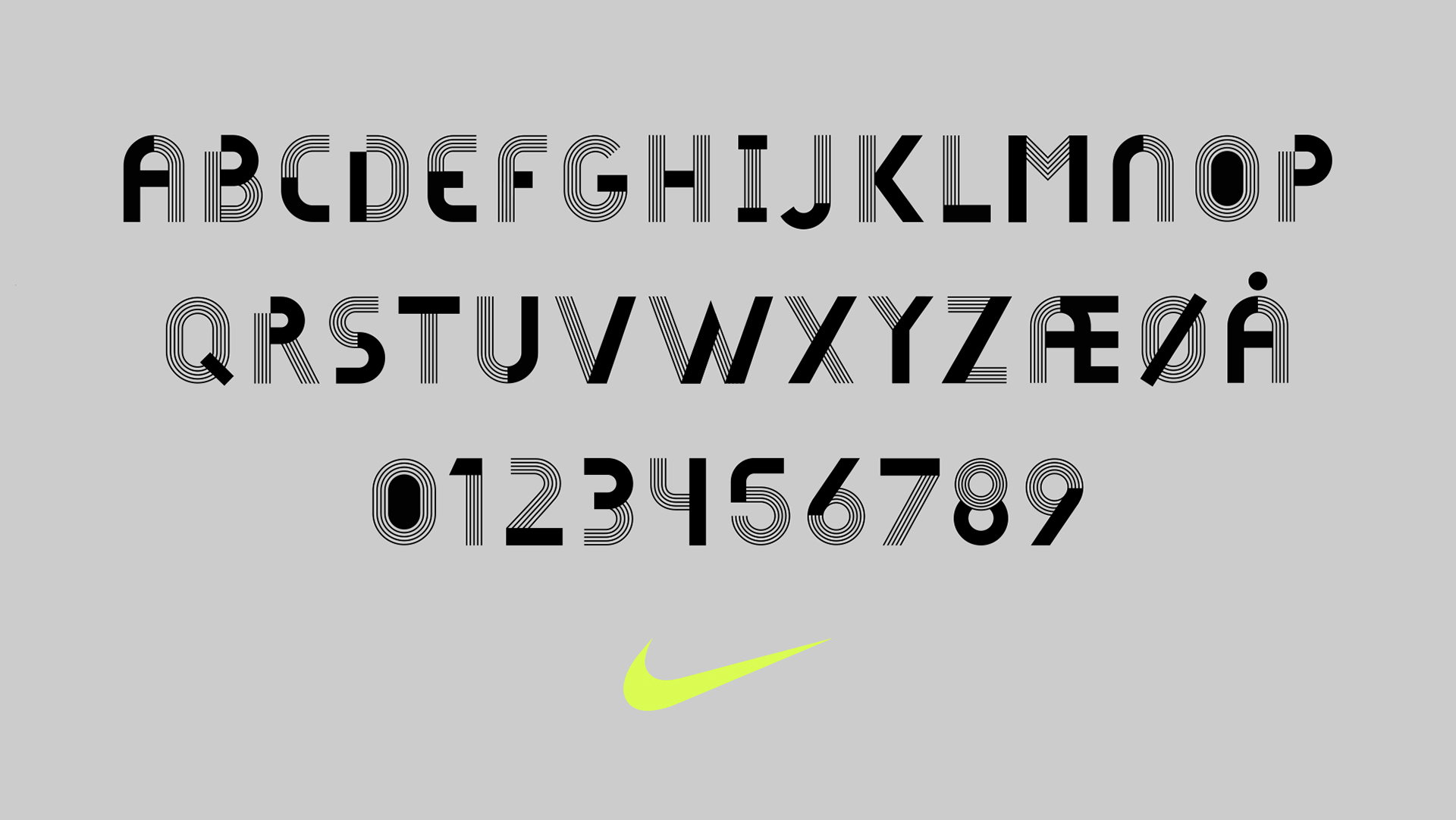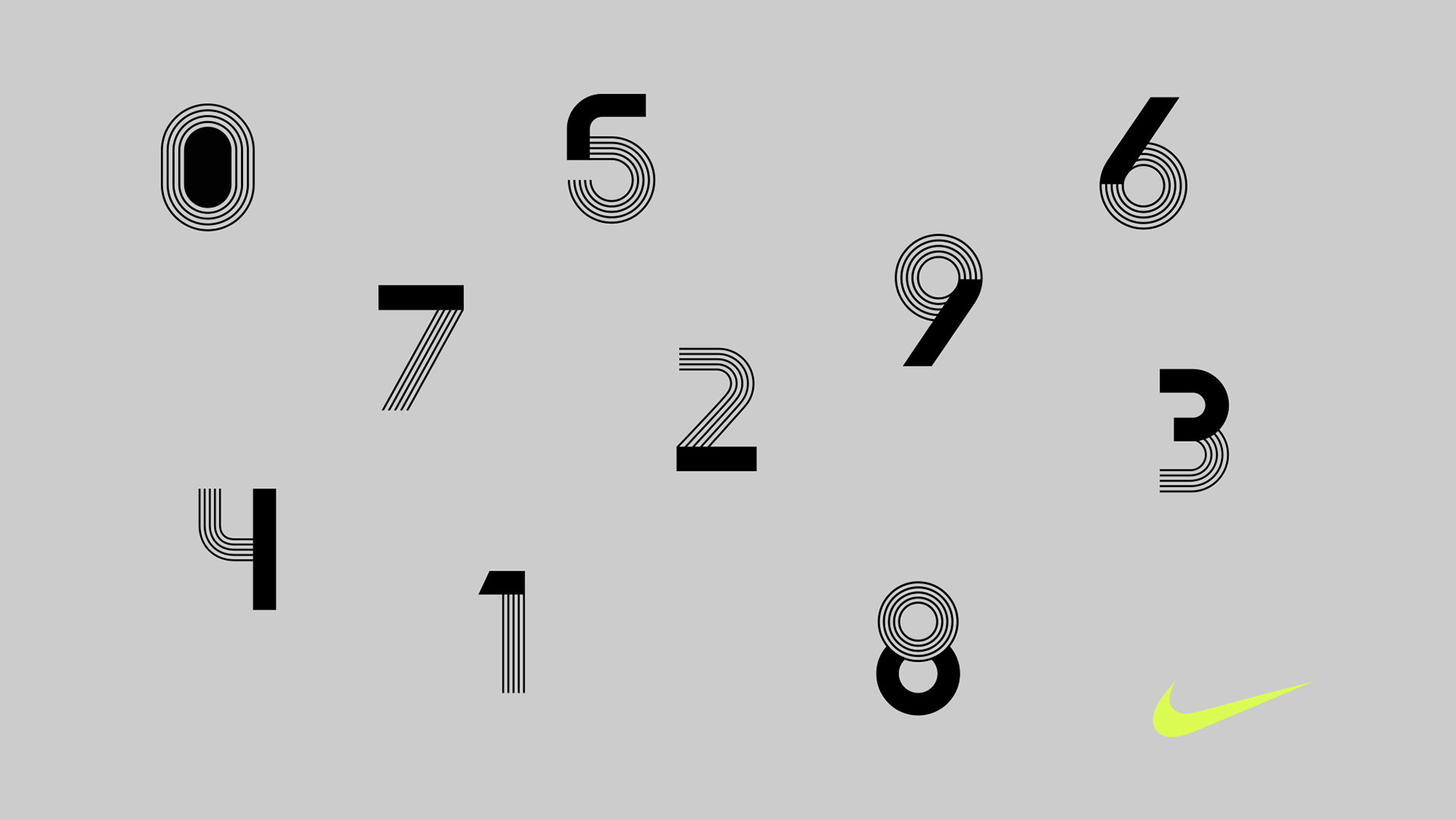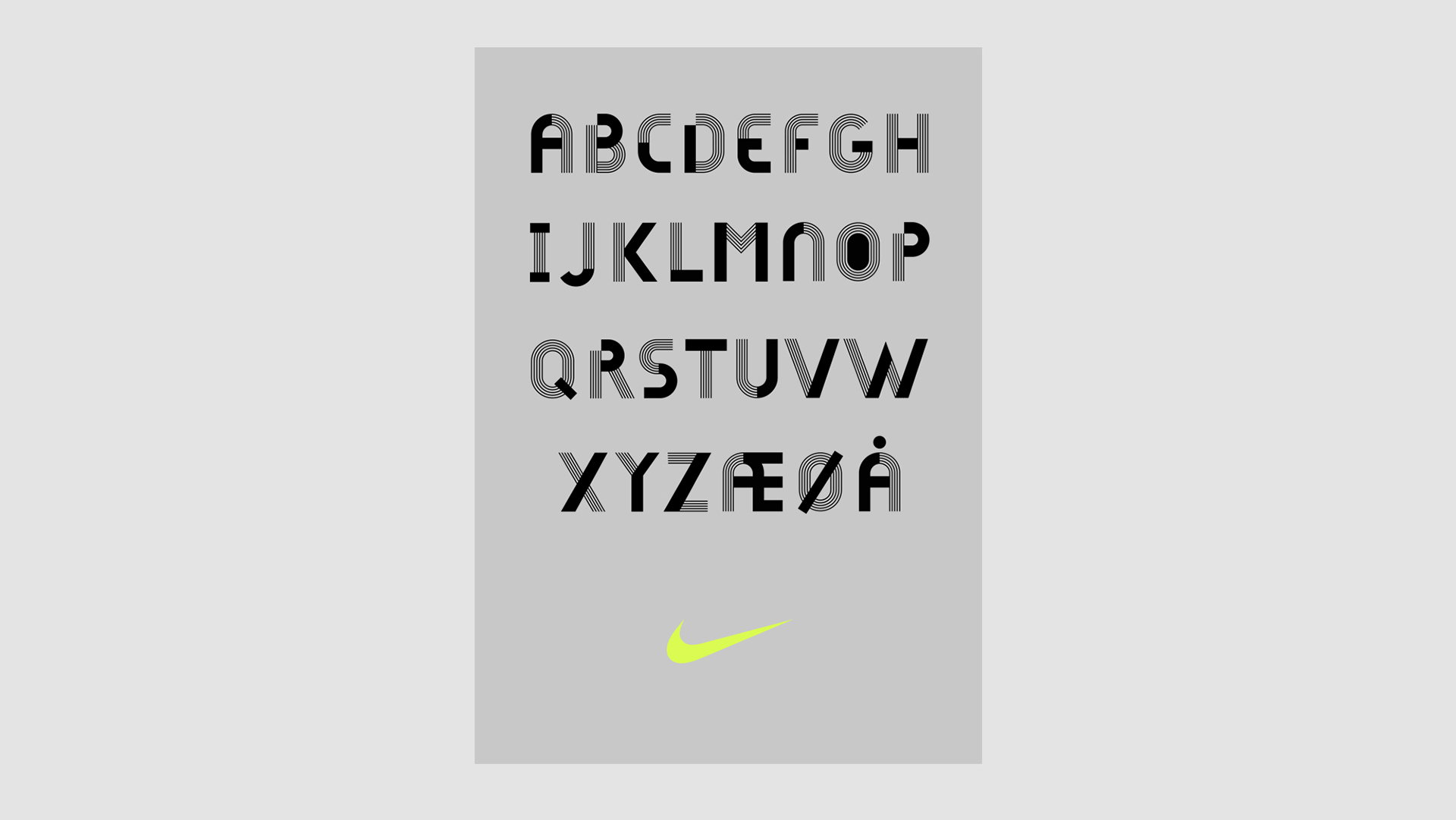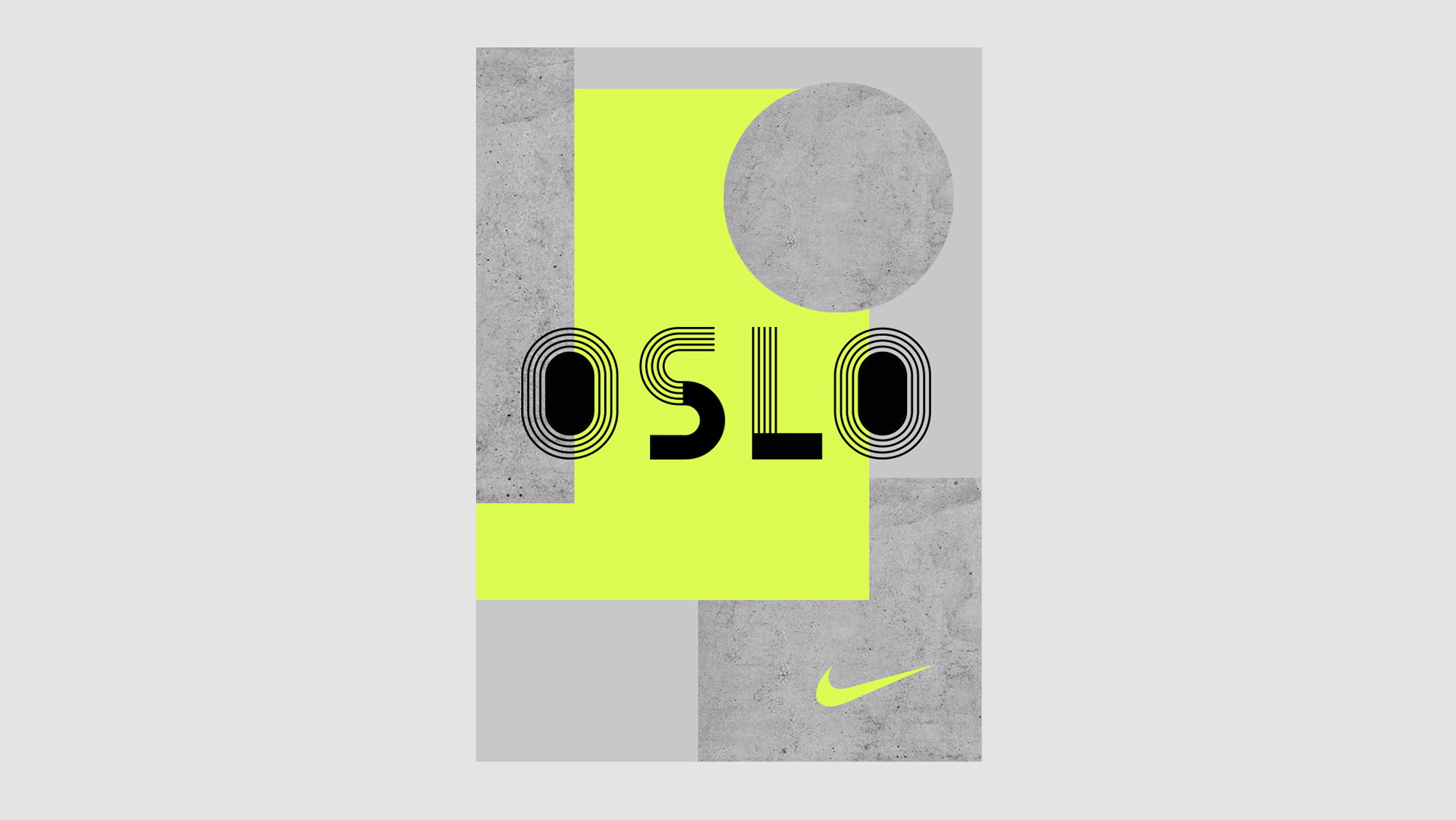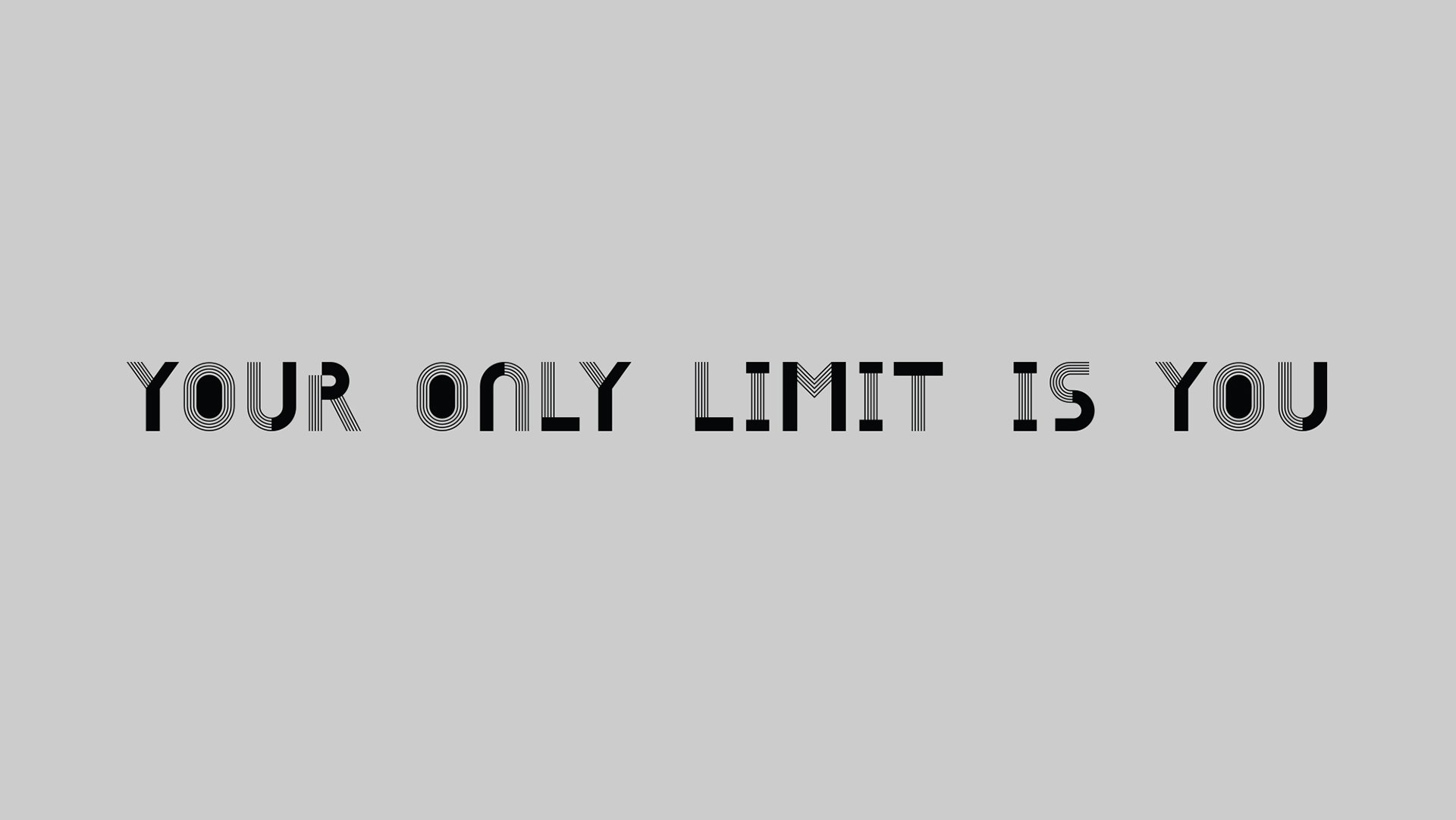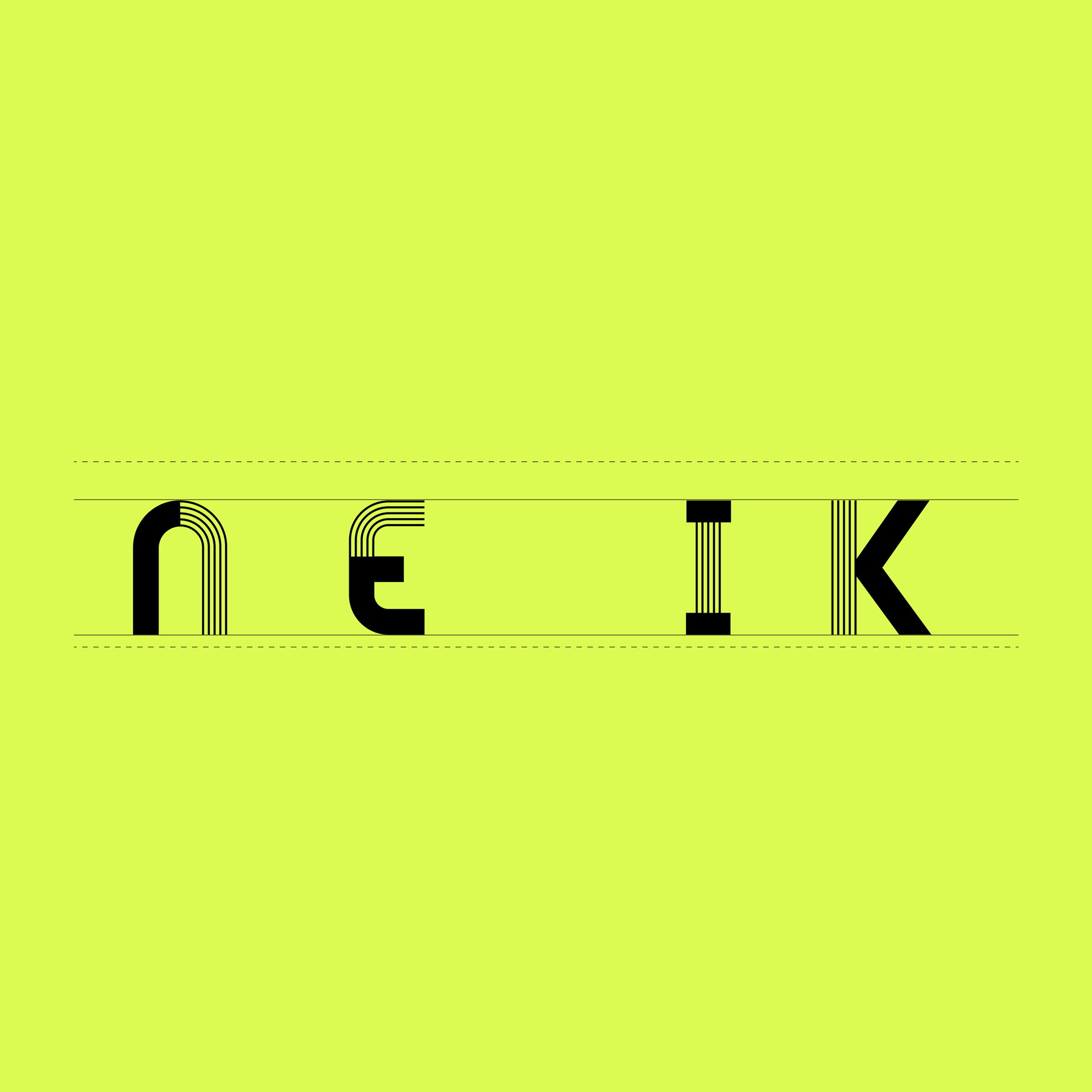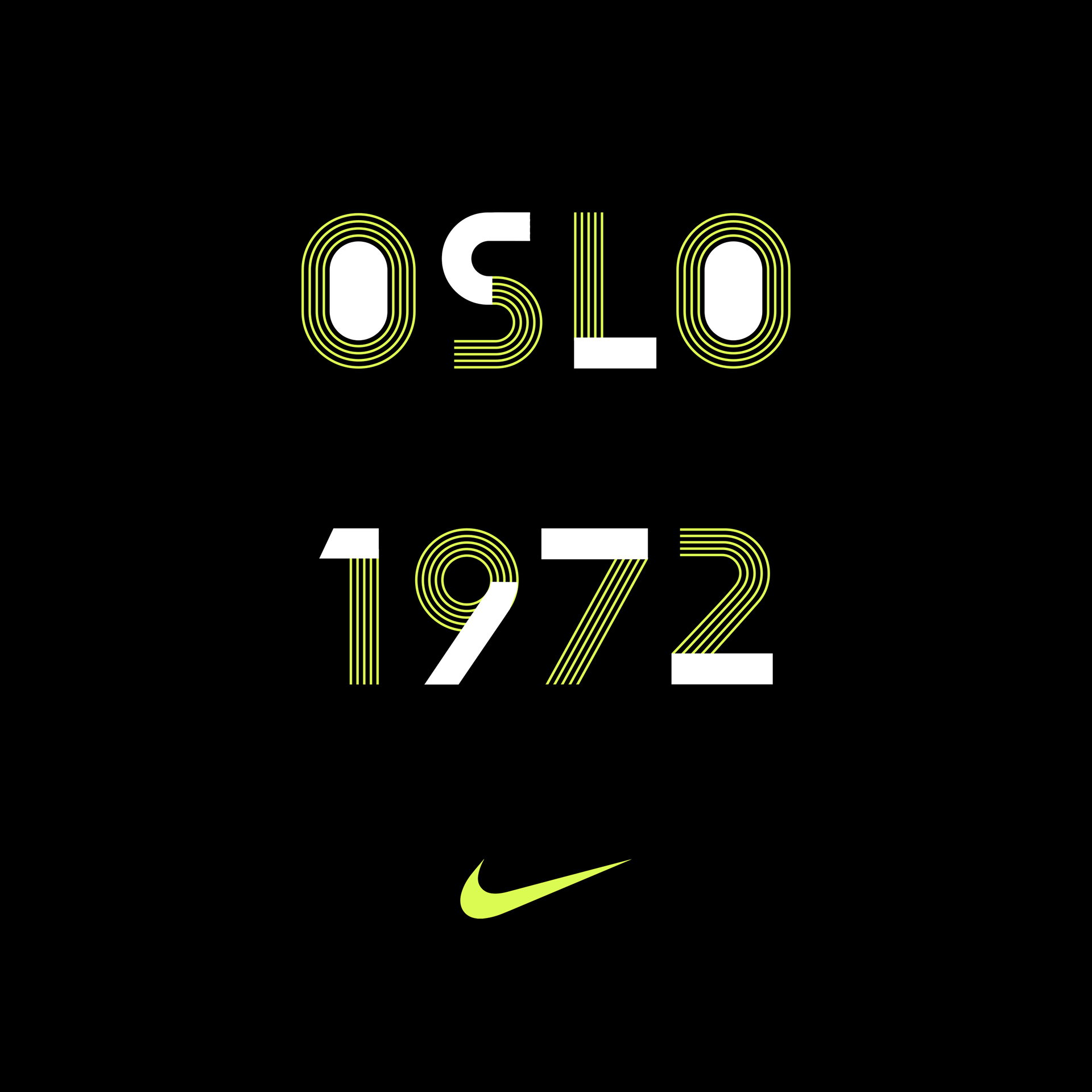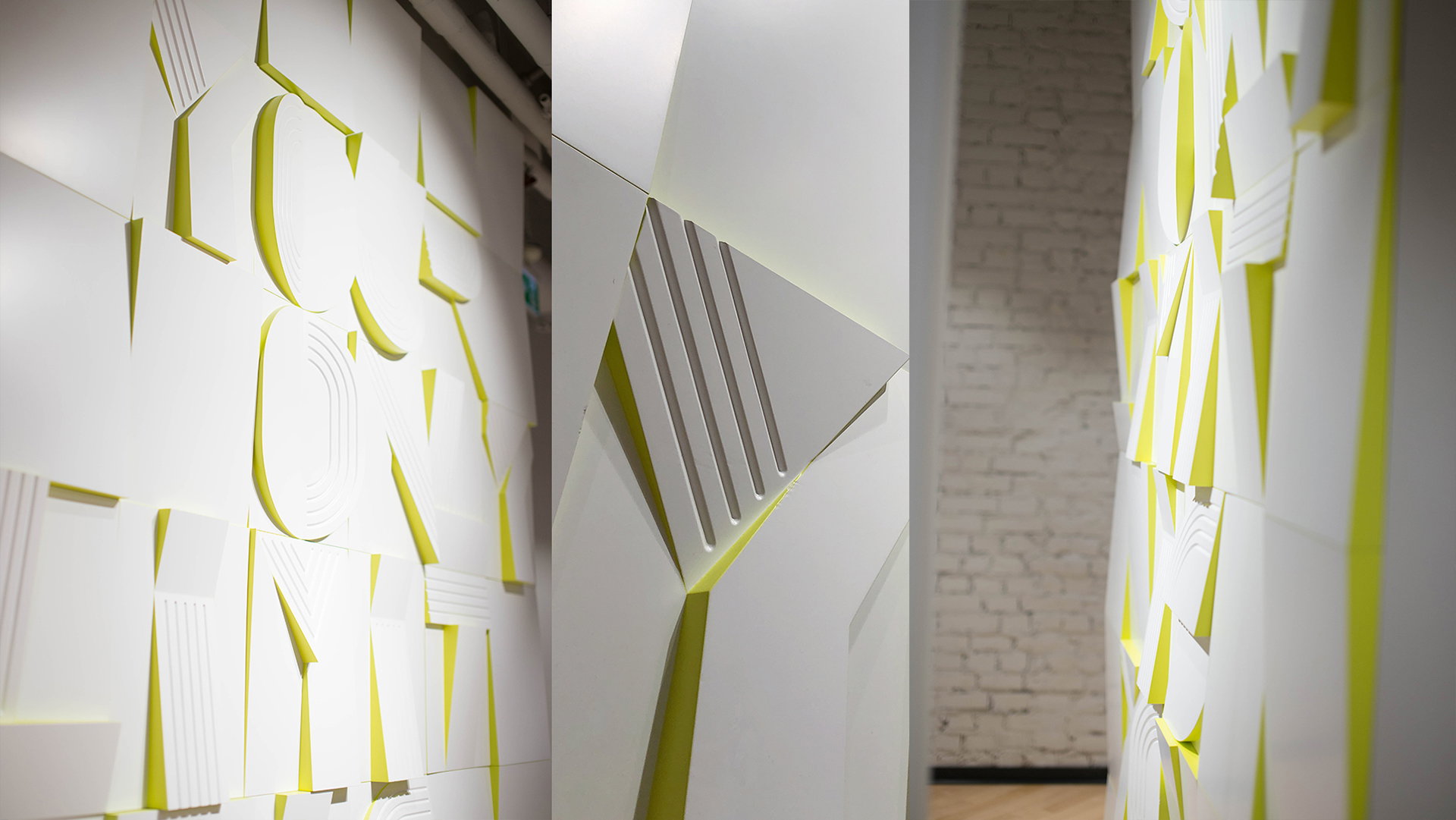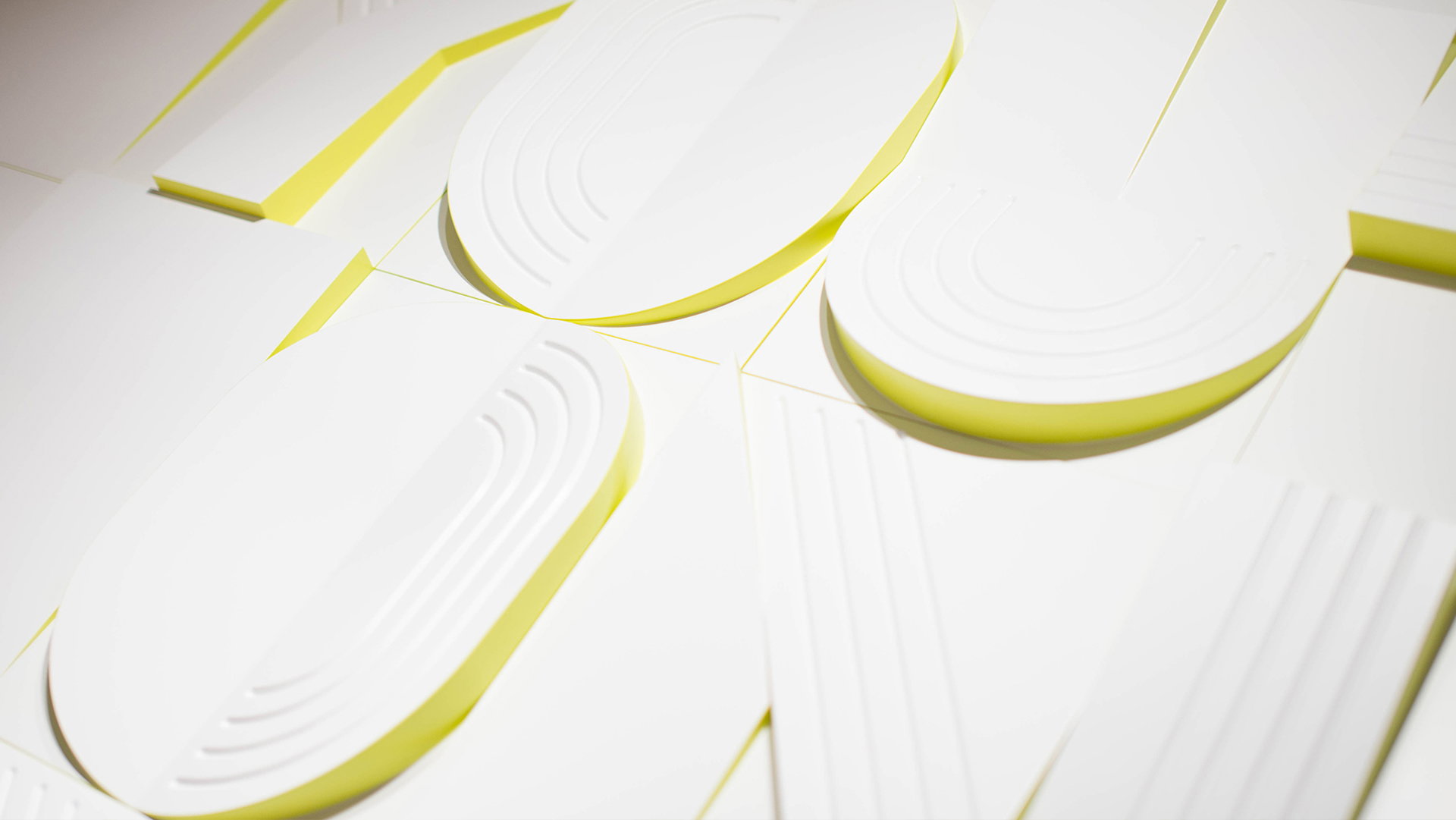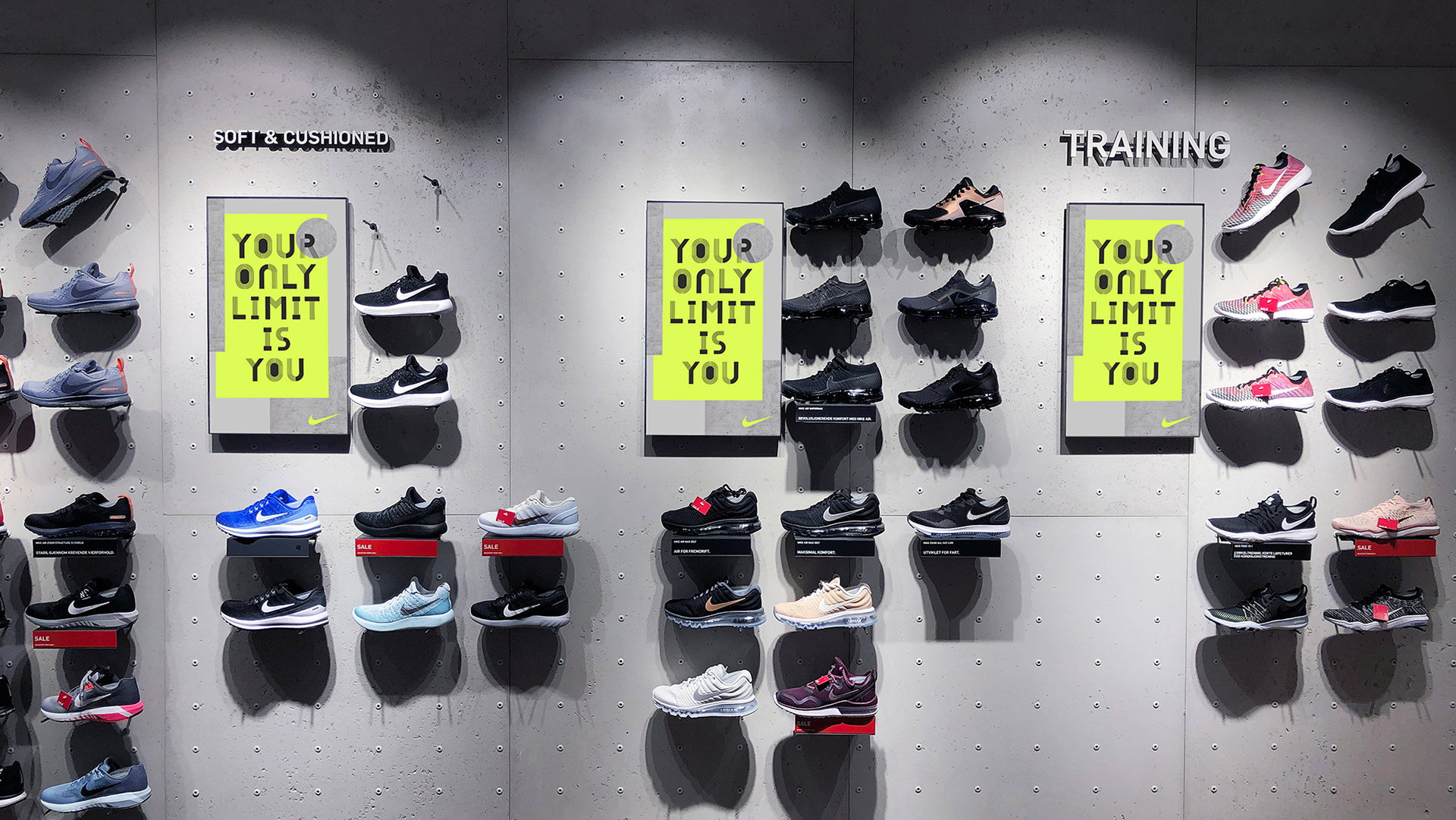
Kan Oslo oppsummeres i en font?
Kan identiteten til en hel by fanges i en font? Og enda viktigere: hvor begynner man å lete etter inspirasjon? «I Oslos gater, selvfølgelig»
– Noe av det mest spennende med typografi er at det kan beskrive en bedrifts verdier, innholdet i et magasin, hva butikken selger eller et produkt underbevisst, lenge før man har rukket å reflektere over hva innholdet er eller hva butikken selger.
Inspirasjonen til den nye typografien for Nike fant han på Bislett Stadion. Etter mye vandring, speiding og grubling var det de karakteristiske linjene fra løpebanene som ble utslagsgivende for det kreative uttrykket.
– Bislett har en sentral plass i Oslos historie som en internasjonal arena for sport og folkefest, på høyde med ikoniske Holmenkollbakken. Linjene fra løpebanen la grunnlaget hele typografien, forteller designeren.
Hard konkurranse
Konkurransen om kundenes oppmerksomhet er like hard som mellom verdensstjernene på 100 meter sprint. Og for sportsbransjens fremste aktører er det bare pallplassering som gjelder. Da må man kontinuerlig satse på nye, spennende prosjekter, mener Øren.
– I fremtiden kan ikke butikker forvente at det er nok å servere rad på rad med passive produkter. De må fortelle historier godt forankret i lokalmiljøet, og bedriftens visjon. Man må skape en opplevelse, en grunn for folk til å sette av tid til å være fysisk tilstede, presiserer Øren.
Casefilm fra Babusjka
Med på laget hadde Øren film- og motionbyrået Babusjka fra Oslo. De har komponert en lekker casefilm av prosjektet og fikk nesten frie tøyler til å tolke konsept og løsning. Filmen er en abstrakt lyd-visuell reise gjennom et løp fra start til slutt. Ved å bruke designelementer fra typografien «Oslo» gjengir den kampen om å vinne løpet, men også den indre kampen om å ikke miste fokus og å bevare roen.